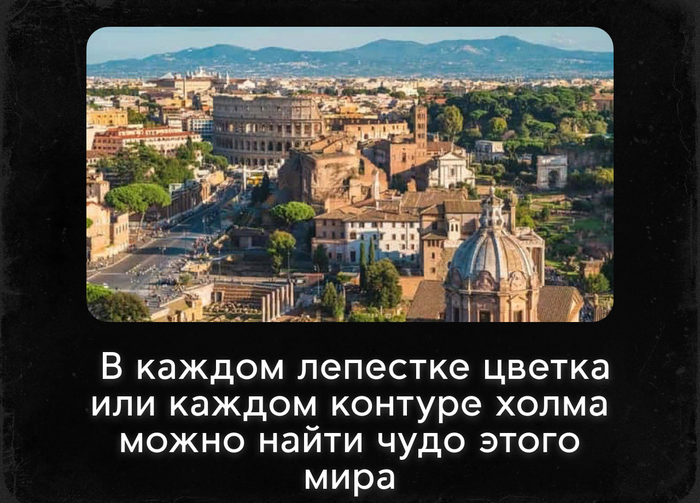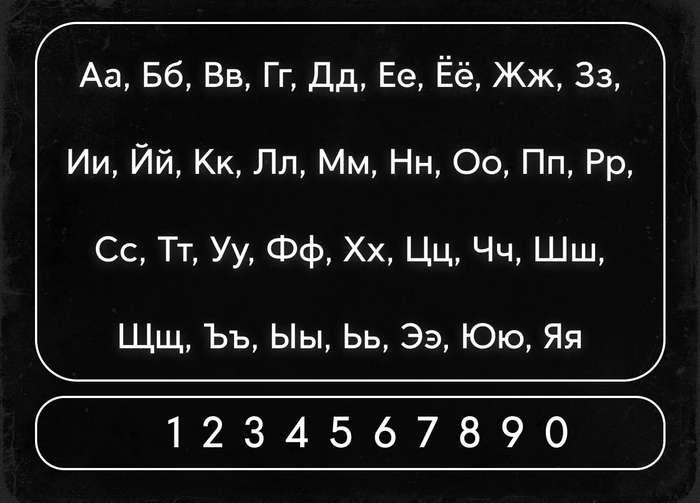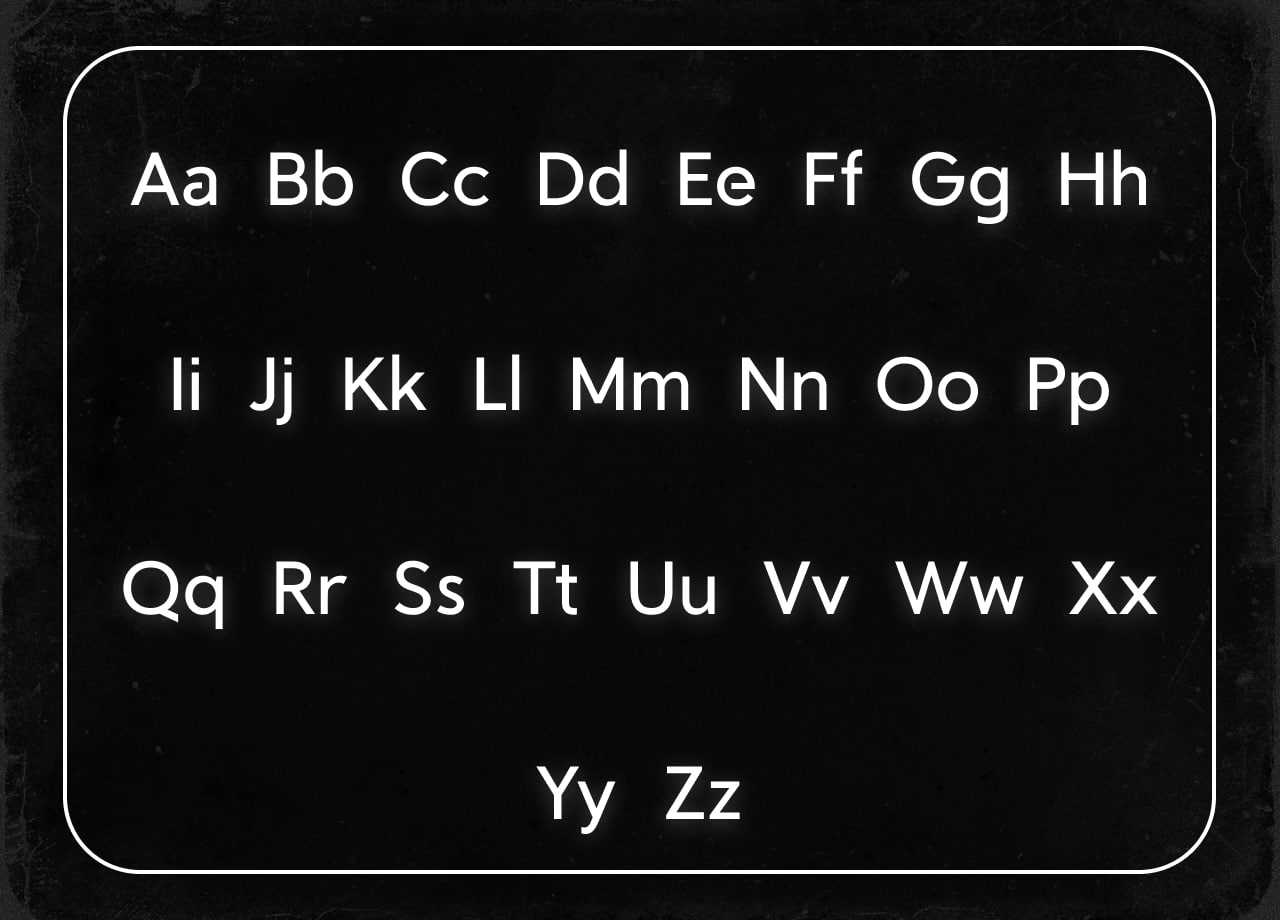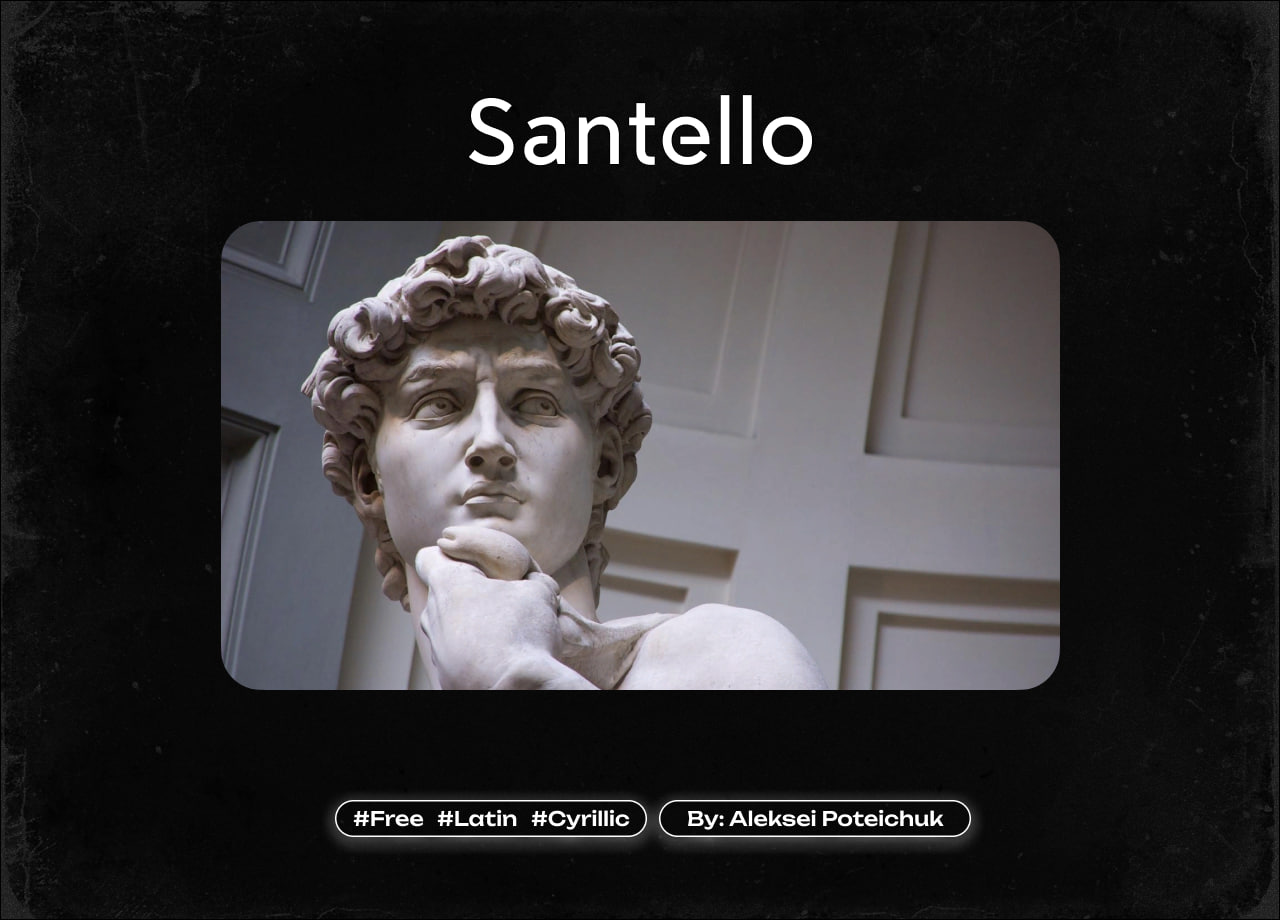
Шрифт Santello. Кириллица + Латиница
Santello - это элегантный скриптовый шрифт, который обычно используется для дизайна открыток, пригласительных, логотипов и других элементов дизайна, где требуется элегантный и изысканный вид. Он имеет изящные завитки и уникальные характеристики, которые придают тексту роскошный и ручной вид.
Начертание только Regular. Хреново